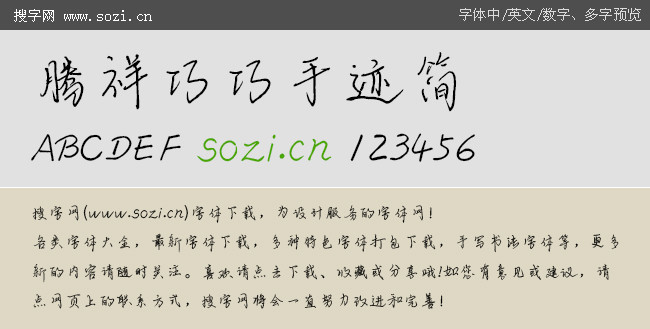
騰祥巧巧手跡簡
搜字網(wǎng)提供一款騰祥巧巧手跡簡中文藝術(shù)字體下載,騰祥巧巧手跡簡是一款很漂亮的手寫字體,書寫風(fēng)格自然流暢,獨具風(fēng)格,稚拙中透顯出活潑靈動的氣息;無雕琢,無拘束質(zhì)樸的視覺效果,用于正文更體現(xiàn)出手寫自然之感。字體可以廣泛應(yīng)用于印刷出版、包裝設(shè)計、廣告設(shè)計、網(wǎng)頁設(shè)計等領(lǐng)域。